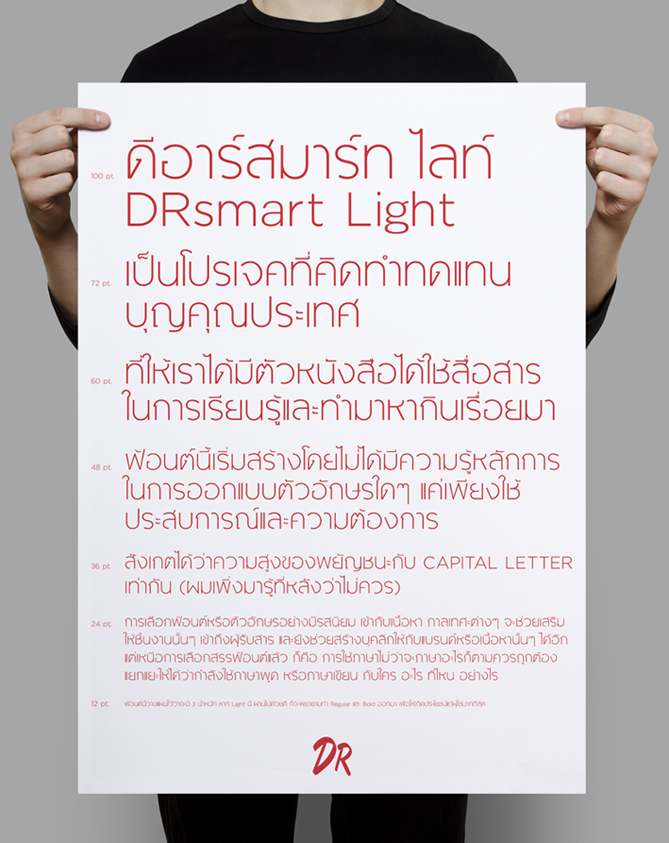
Font DRsmart
DR
มาหย่อนไว้ก่อนนะครับ เพิ่งแปลงเป็นฟ้อนท์แล้วทดลองพิมพ์จัดวางดู ขอไปปรับช่องไฟทั้งหมด แล้วจะเอามาให้ดูเพิ่มเติมครับ (ขอบคุณคุณเอส ed_club ที่ให้คำแนะนำหลายอย่าง และคุณแอนที่ช่วยเช็คการสมัครสมาชิกให้ครับ)
เพิ่มเติมให้นะครับ
ตัวอักษรเรียงตาม Glyph ใน Illustrator
โอววว  สวยยยย  :25: :25:
ปล ผมติดที่สระแอ ครับ ดูรวมๆมันเป็นปื้นๆ สะดุดตาไปนิดครับ  :46:
ขอบคุณสำหรับคำแนะนำครับ ตอนนี้ก็รวบรวมจากเพื่อนผมมาด้วย ที่จะปรับ ดังนี้...
สระอิ อี อึ อื วรรณยุกต์ทั้งบน ล่าง ที่จะปรับขนาดและความชัดเจน
สระแอ จากคุณ Layiji
*หากท่านอื่นมีความเห็นอย่างไร บอกไว้ได้นะครับ เพื่อประโยชน์จะได้นำ font นี้ไปใช้ด้วยกัน
อยากดู Latin ทั้งชุดครับผม ตัวไทยเรียบง่ายดีฮะ
คุณ rootEngineer หมายถึง ตัวอักษรทั้งหมดเลยรึเปล่าครับ ในภาพสุดท้าย จะมีทั้งหมดแล้วครับ หรือถ้าผมเข้าใจผิด บอกนะครับ ว่า Latin ที่ว่าหมายถึงอะไร
หมายถึงตัวอักษรละติน (อังกิดและอื่นๆ ที่มีเค้าเดียวกัน) ทั้งหมดครับ ที่ผมดูรวมๆ แล้วขัดหูขัดตาคือ
- ผมเห็นแค่ œ แต่ไม่เห็น Œ นะครับ
- í î Í Î มันติดกันจนมองแทบไม่ออกแฮะครับ แต่ยังไงพิมพ์เป็นคำคงไม่พิมพ์ติดสองตัวกันอยู่แล้ว
- æ เห็นมีหางของ a เล็กๆ แล้วมันดูแปลกๆ ฮะ (ไม่รู้ว่าผมรู้สึกไปคนเดียวหรือเปล่า?)
- ทำ × ÷ ไหมครับ อยากเห็นเมื่อจัดอยู่กับตัวเลข
ก็ว่าดูแบบกันจากไหน ที่ไหนได้คุณดำรงใส่ภาพเพิ่มไว้ข้างบนนี่เอง :3005:
เรื่องความสูงของตัวอักษรไทย-ละติน อย่าได้ซีเรียสครับ เอาที่ใช้แล้วสะดวกเลย
มาตรฐานที่ออกมานั้นเขาทำไว้เพื่อความสะดวกในบางอย่างครับ แต่ดีไซเนอร์สามารถกำนดวิถีของฟอนต์ได้เอง
เดี๋ยวรอดูเรื่อยๆ นะครับ งานสวยมาก :12:
ปรับมาให้ดูอีกครั้ง ตามที่สรุปไว้คราวก่อน
สวยงามเลย พวกสระบนยังติดอยู่อีกนี้ดครับ ยกขึ้นไหวไหมครับ :12:
สระอะ มันชิดกันไปหน่อยไหมครับ น่าจับมันถ่าง บน-ล่าง อีกซักกะนิด
สวดยวดเลยครับ  :25: :25: :25:
ปรับตามที่แนะนำกันอีกครั้งครับ
อร่อยขึ้นมาก :25: